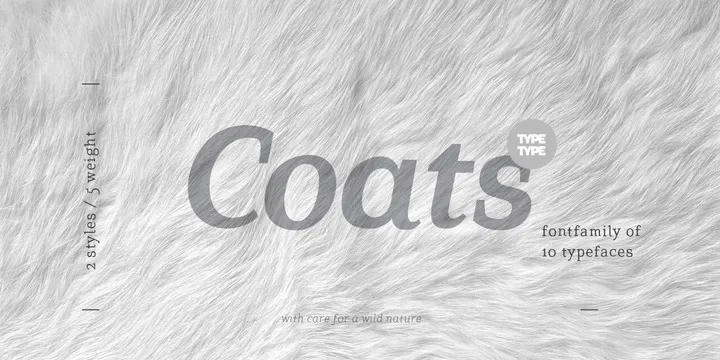
A TT Coats é uma linda slab serif que foi criada com carinho, inspirando-se no haptic touch dos anseios humanos. Seu charme cuidadosamente escrita dá vida a pequenos recortes emocionais. TT Coats vai aquecer seu dia frio e enche de bondade qualquer layout. Além disso, as linhas digitadas com essa fonte começam a tremer em textos longos, então é sempre bom ser cauteloso e usar esta família para ocasiões especiais e pequenas quantidades. É uma fonte única que traz leveza e suavidade às suas criações gráficas.